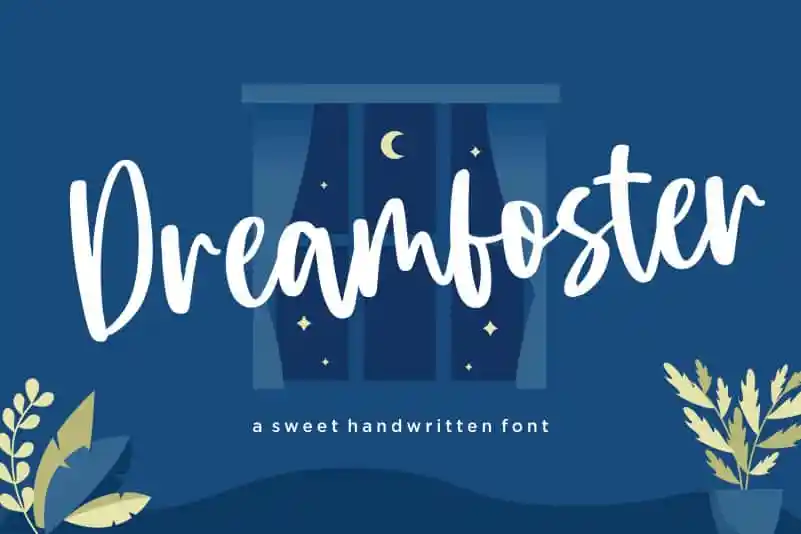
Dreamfoster Sweet Handwritten Font – Download Grátis
A fonte ‘Dreamfoster Sweet Handwritten Font’ é perfeitamente adequada para projetos digitais que valorizam a personalidade e a emoção. Suas linhas delicadas e traços suaves criam um estilo elegante e acolhedor, tornando-a uma escolha ideal tanto para aplicações de packaging quanto para criações de marca. Com seu charme único, essa fonte se destaca em projetos como revistas, redes sociais, editoriais de casamento ou qualquer outro momento onde você deseja destacar o texto sobre um fundo. Com a sua versatilidade e apelo visual, ‘Dreamfoster Sweet Handwritten Font’ é uma fonte perfeita para expressar sentimentos e ideias através do texto. Suas linhas suaves oferecem aos designers e criadores de conteúdo a oportunidade de fazer seus textos se destacarem em qualquer mídia digital ou impressa. É especialmente adequada para momentos especiais onde você deseja transmitir emoção, como editoriais de casamento e campanhas publicitárias. Agora é hora de deixar sua marca com um toque delicado e poético!